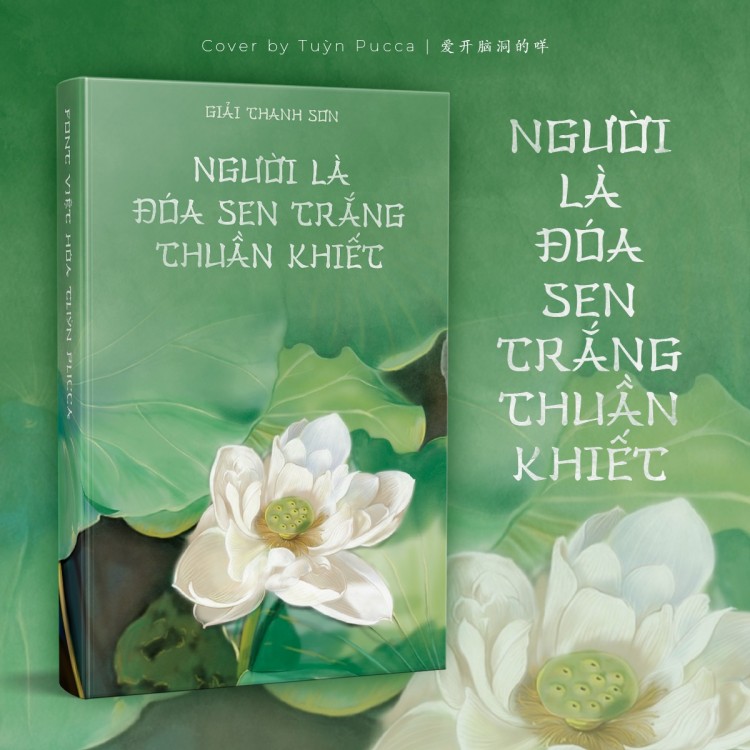
Trong thế giới thiết kế đồ họa hiện đại, việc lựa chọn một bộ Font Chữ phù hợp đóng vai trò quan trọng để truyền tải thông điệp văn hóa. Font việt hoá TP Han Zi phong cách nhật bản là một sự lựa chọn tuyệt vời dành cho những ai yêu thích vẻ đẹp thanh tao, tinh tế của thư pháp Á Đông. Bộ font này không chỉ giữ nguyên được cái hồn của nét bút lông truyền thống mà còn được tối ưu hóa hoàn toàn cho bảng mã tiếng Việt, giúp người dùng dễ dàng ứng dụng vào nhiều loại hình thiết kế khác nhau từ học tập đến quảng cáo.
Đặc điểm nổi bật của Font việt hoá TP Han Zi phong cách nhật bản
Nét vẽ mang đậm dấu ấn thư pháp thủ công
Đúng như tên gọi, bộ font này mô phỏng các nét chữ Hán tự nhưng được cách điệu theo phong cách tối giản của Nhật Bản. Các nét thanh và nét đậm được kết hợp hài hòa, tạo ra cảm giác vừa mạnh mẽ lại vừa mềm mại. Đây là công cụ hữu ích cho các bạn học sinh khi thiết kế bìa sách hoặc poster chủ đề văn hóa dân gian.
Khả năng hiển thị và tính tương thích cao
Ứng dụng Font việt hoá TP Han Zi phong cách nhật bản trong thực tế